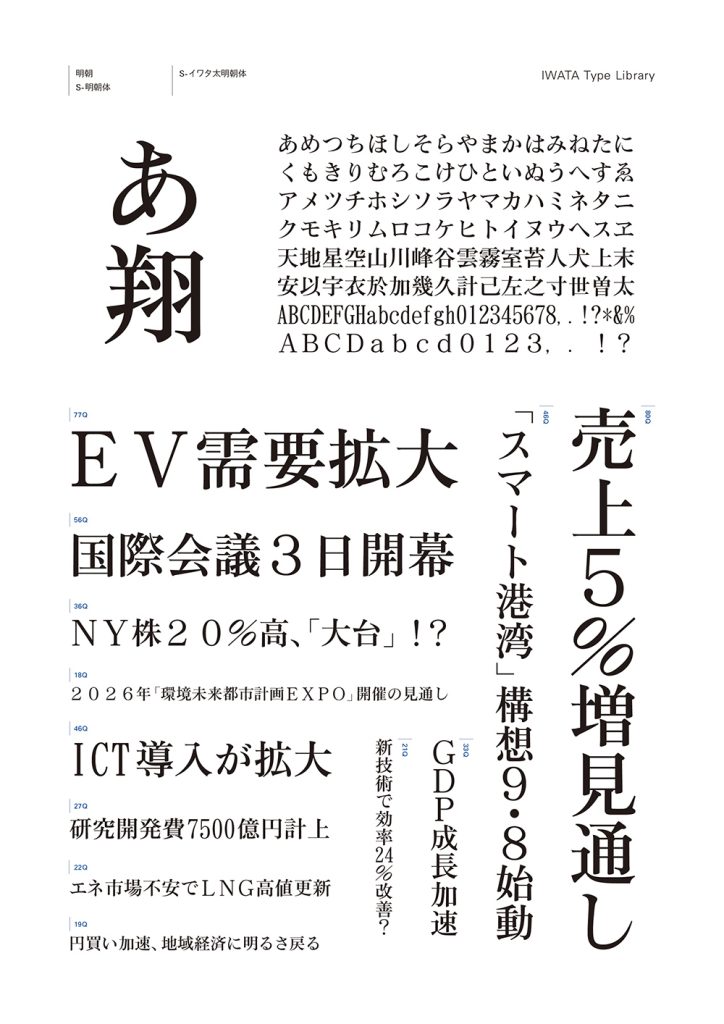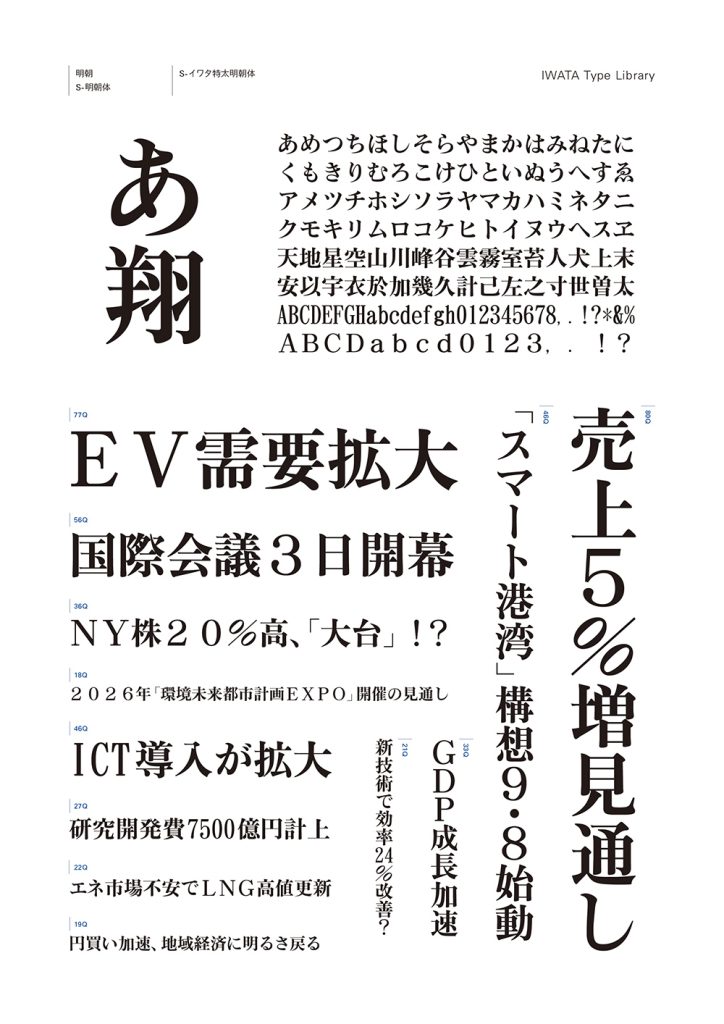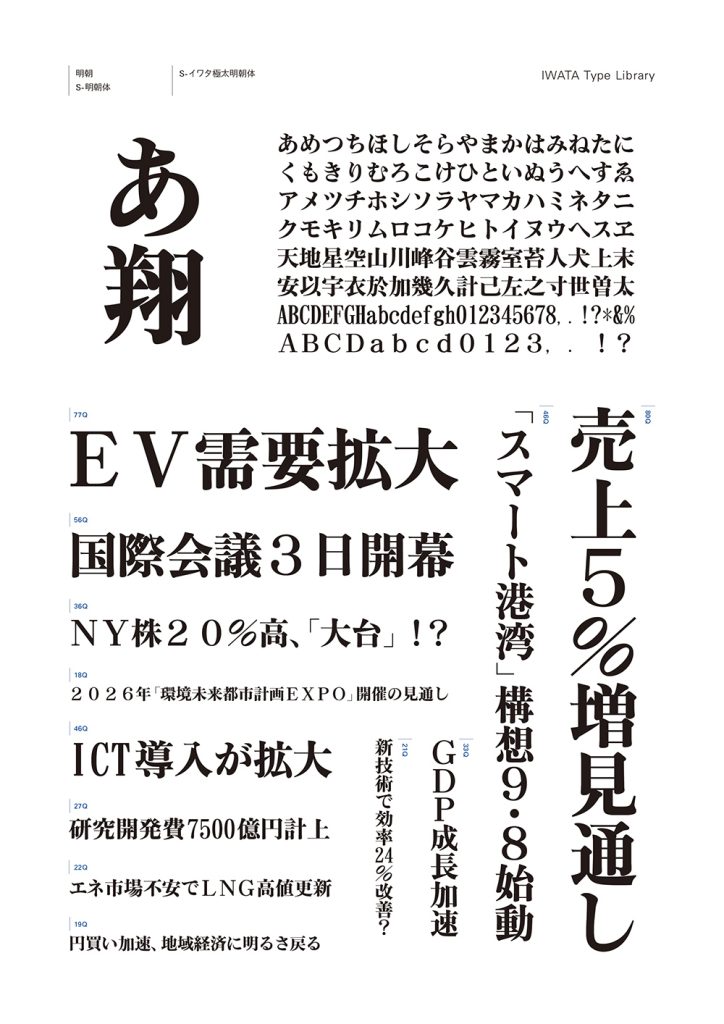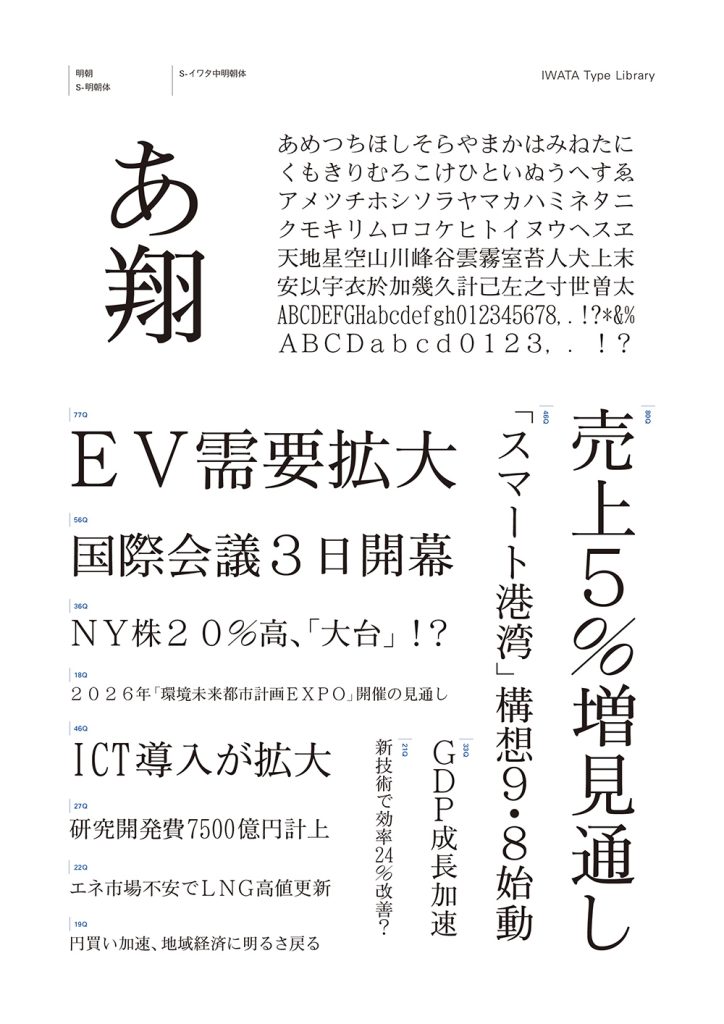
新聞見出し用に最適化された明朝体です。横画始筆の打ち込み、縦画収筆のふくらみなど活字風のメリハリのある力強いデザインにより、見出しに華やかさやインパクトを持たせることができます。文字セットは、共同通信社が新聞制作用に策定した「U-PRESS」に対応しています。
イワタの新聞見出し用書体“S- フォント”とは
約物のデザインや文字の高さなどが、あらかじめ新聞の見出しに最適な状態に調整されたフォントです。細かな調整をせずに美しい見出し組を実現できます。
書体デザインのポイント
新聞の見出し組版に適するよう、デザインに工夫がされています。